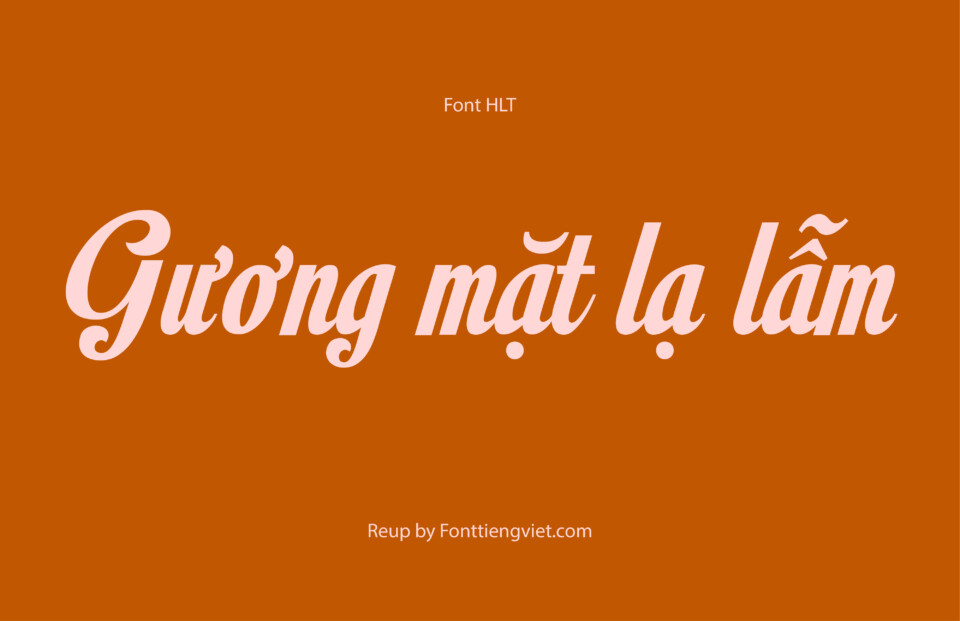
Font Việt hóa HLT Motion Picture
Giới thiệu về Font Việt hóa HLT Motion Picture
Trong thế giới sáng tạo, việc tìm kiếm một bộ Font Miễn Phí chất lượng luôn là ưu tiên hàng đầu của các nhà thiết kế. Font Việt hóa HLT Motion Picture nổi lên như một lựa chọn hoàn hảo nhờ phong cách phóng khoáng và nghệ thuật. Đây là bộ phông chữ thuộc phong cách Script (viết tay) với những đường nét uyển chuyển, mang đậm hơi thở của các tấm biển quảng cáo điện ảnh cổ điển. Việc sử dụng bộ chữ này giúp tác phẩm của bạn trở nên sống động và có chiều sâu hơn bao giờ hết.
Đặc điểm nổi bật của phông chữ
Điểm mạnh nhất của Font Việt hóa HLT Motion Picture chính là sự mềm mại trong từng nét vẽ. Các ký tự được chăm chút tỉ mỉ, đảm bảo tính liên kết tự nhiên như chữ viết tay thật. Với bảng mã Unicode chuẩn, người dùng có thể dễ dàng gõ tiếng Việt có dấu mà không lo lỗi hiển thị. Phông chữ này cực kỳ phù hợp cho các tiêu đề phim, thiết kế bao bì, hoặc các thiệp mời sự kiện quan trọng cần sự sang trọng và tinh tế.
Ứng dụng thực tế của Font Việt hóa HLT Motion Picture
Sáng tạo nội dung đa phương tiện
Nếu bạn đang thực hiện các dự án video hoặc banner quảng cáo, Font Việt hóa HLT Motion Picture sẽ giúp thông điệp truyền tải hiệu quả hơn. Khả năng tương thích tốt trên các phần mềm như Photoshop, Illustrator hay Canva giúp quy trình làm việc trở nên mượt mà. Đặc biệt, trong môi trường giáo dục, thầy cô và học sinh có thể dùng bộ phông này để trang trí slide thuyết trình thêm phần bắt mắt và chuyên nghiệp.